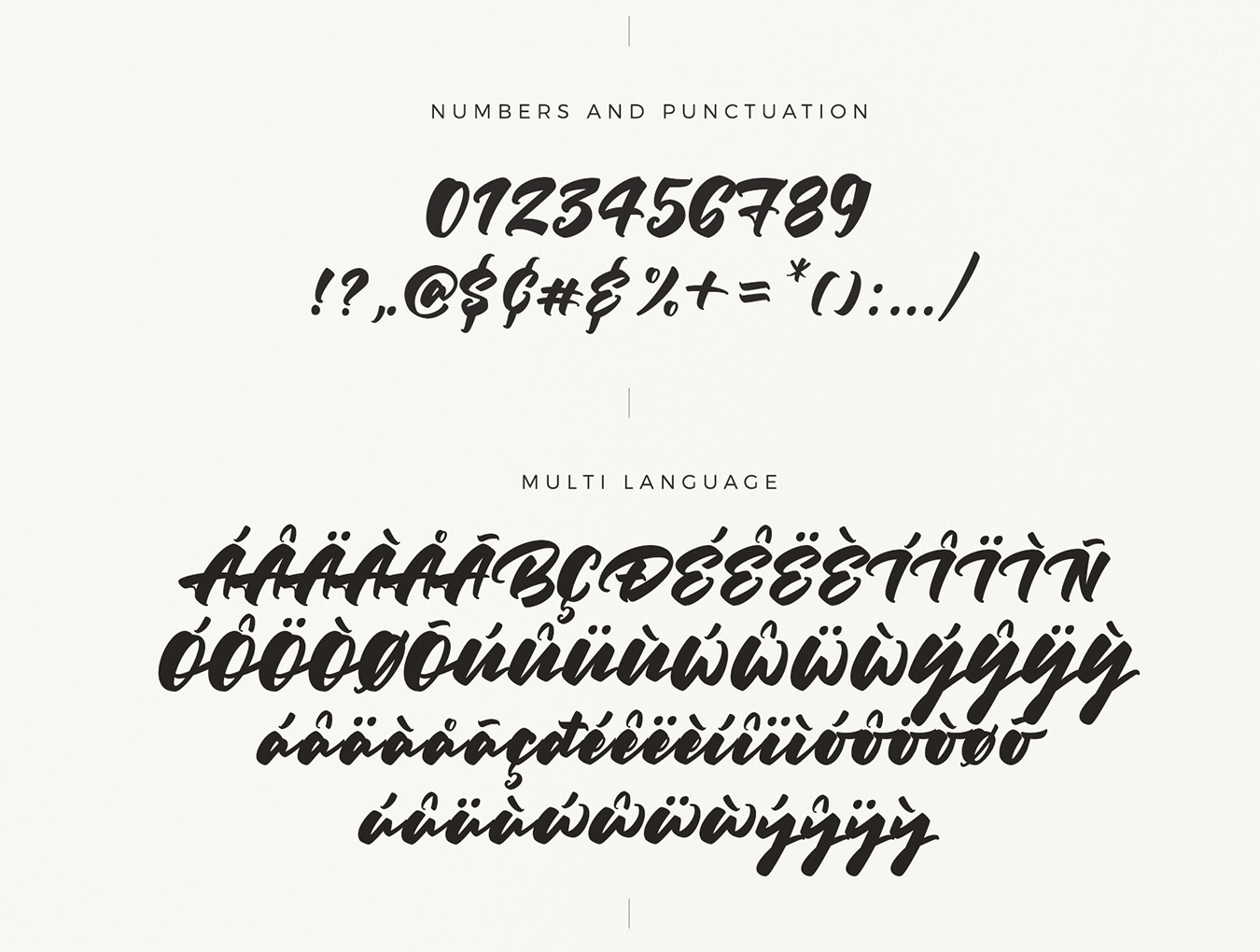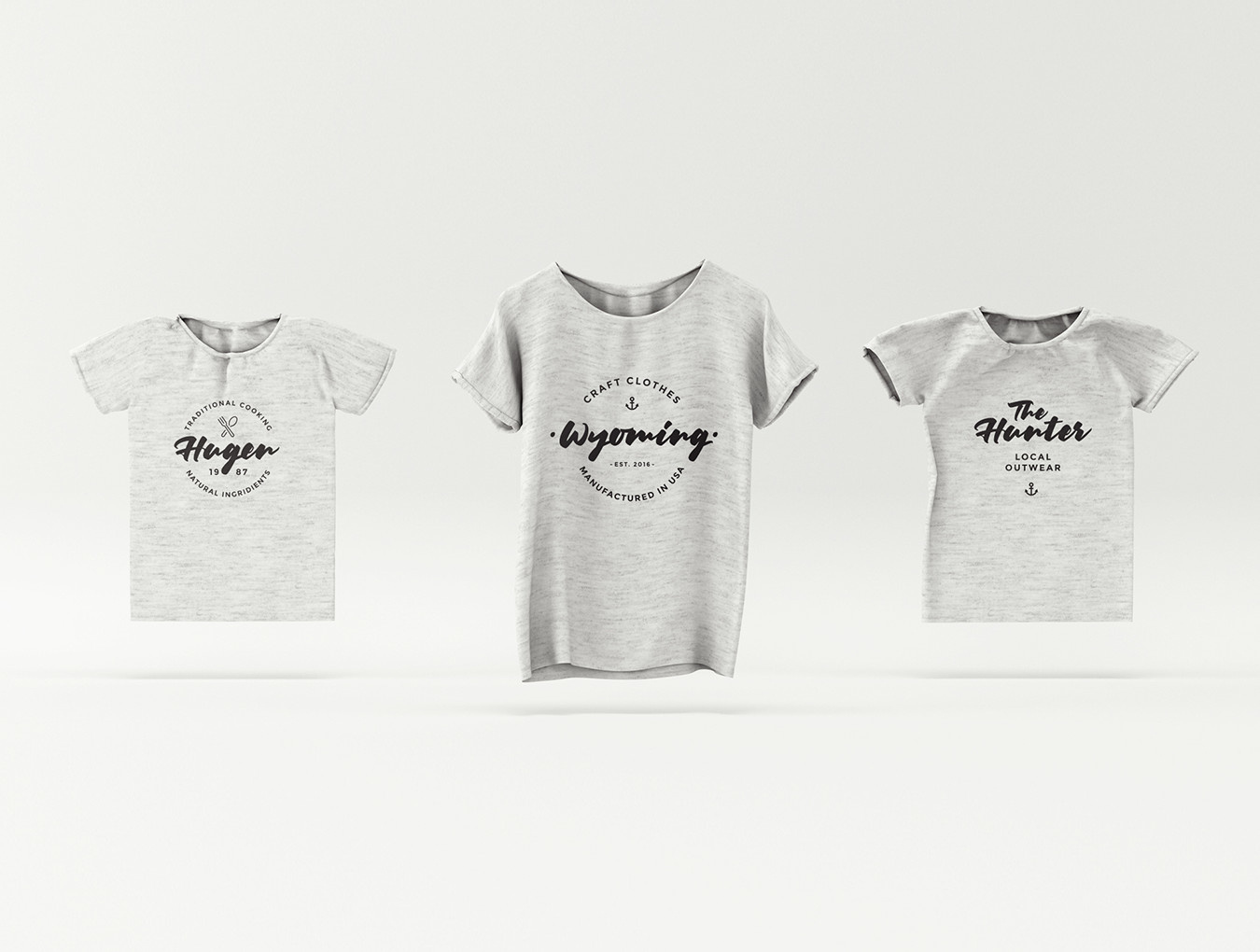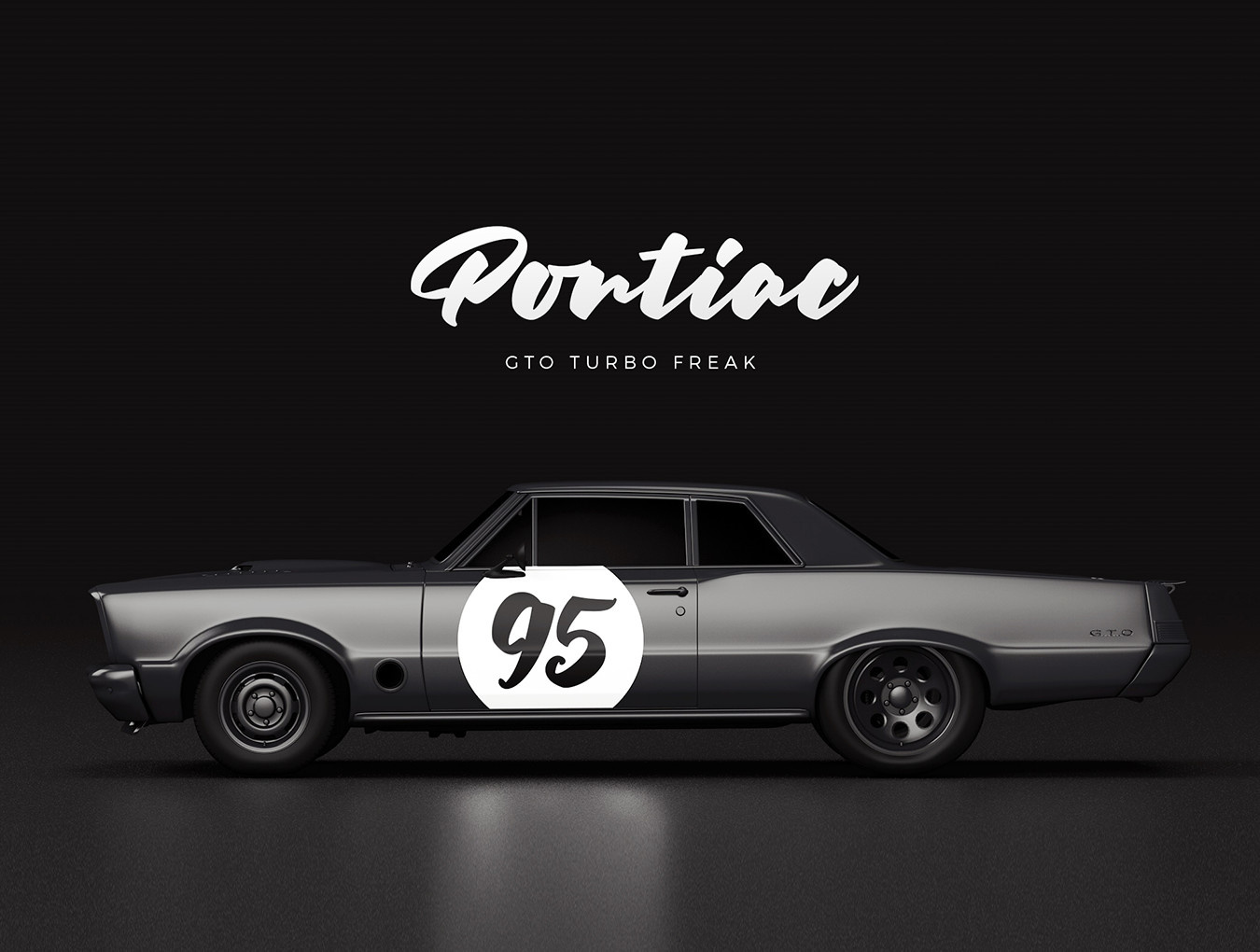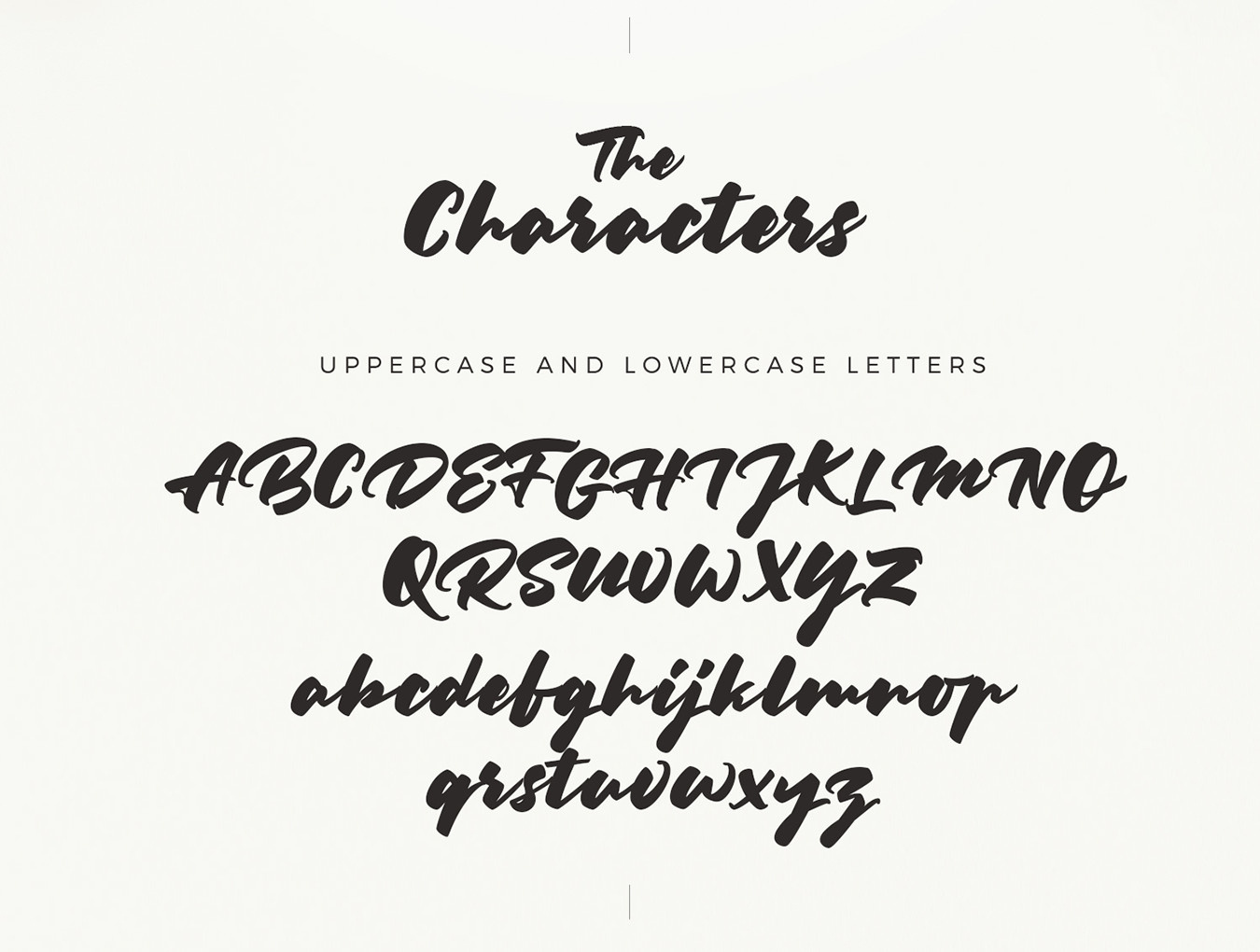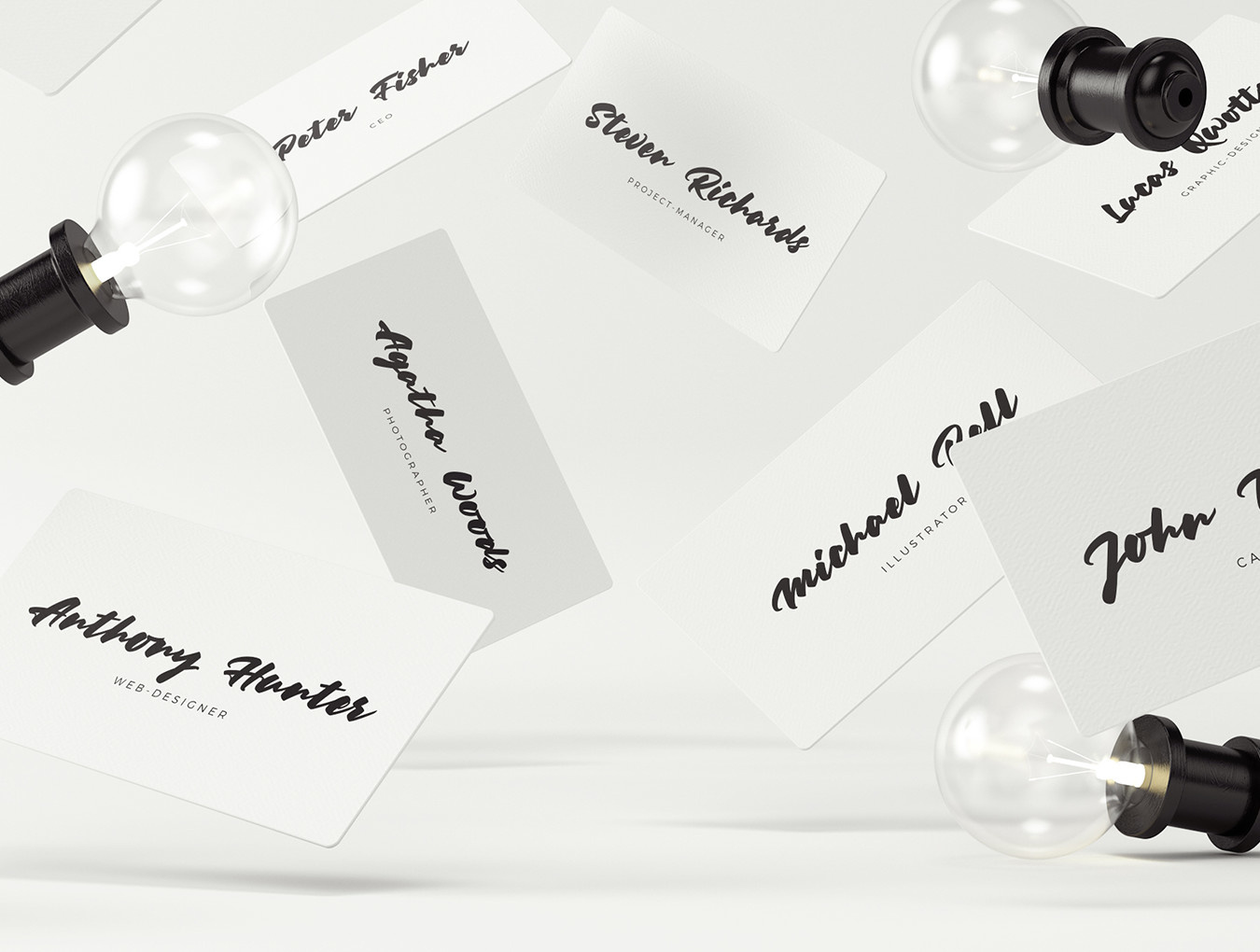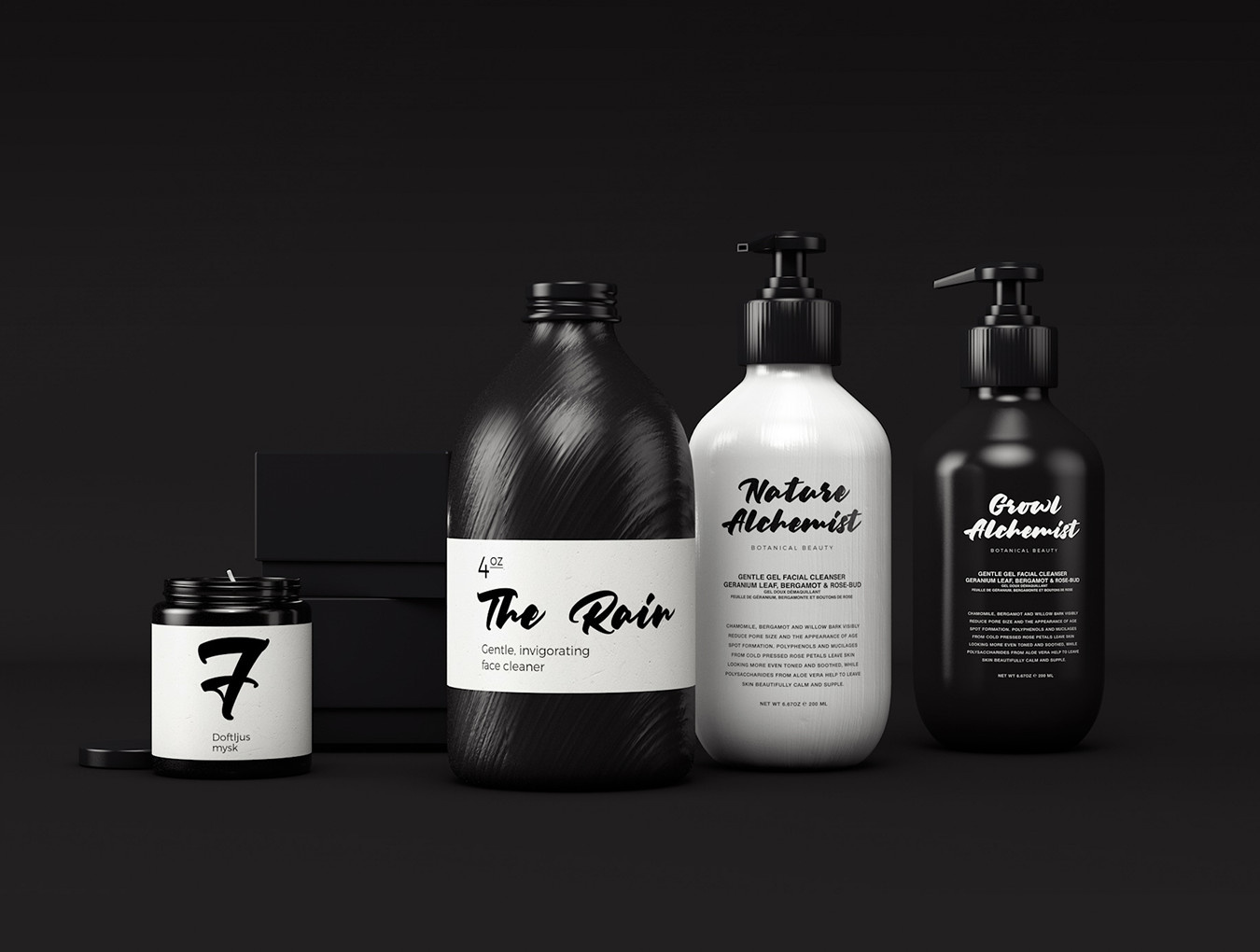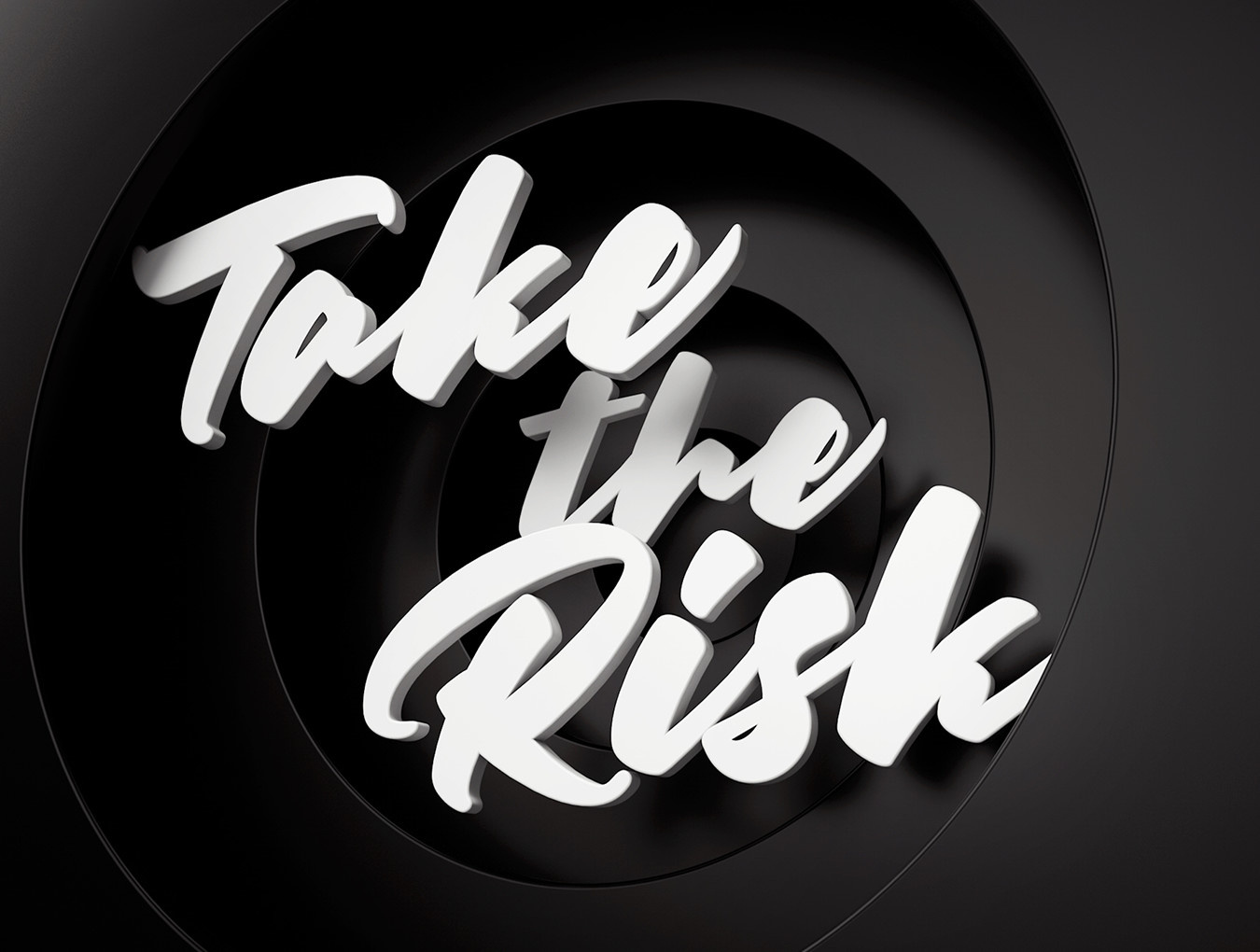
您的品牌的完美脚本字体,Keyline脚本字体
Perfect Script Font for your Branding, Keyline Script Font
Keyline配有一整套大小写字符 - 让您可以自由地将文字转换为真正的定制手工字母。 Keyline字体包括大量字形,包括数字,标点符号和多语言支持。